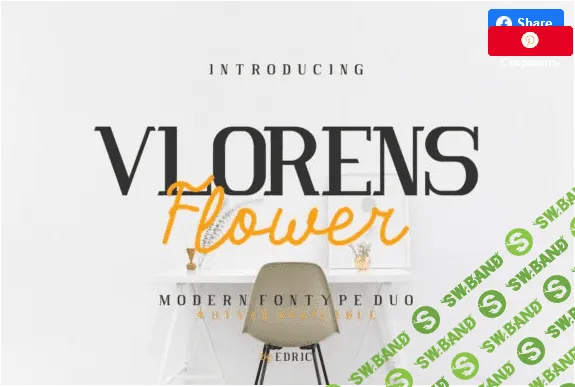
Название: Vlorens Flower Duo Font (2022)
Vlorens Flower — это современный и стильный дуэт шрифтов с классным ощущением. Вдохновитесь его современной эстетикой и превратите любой дизайнерский проект в настоящий шедевр!